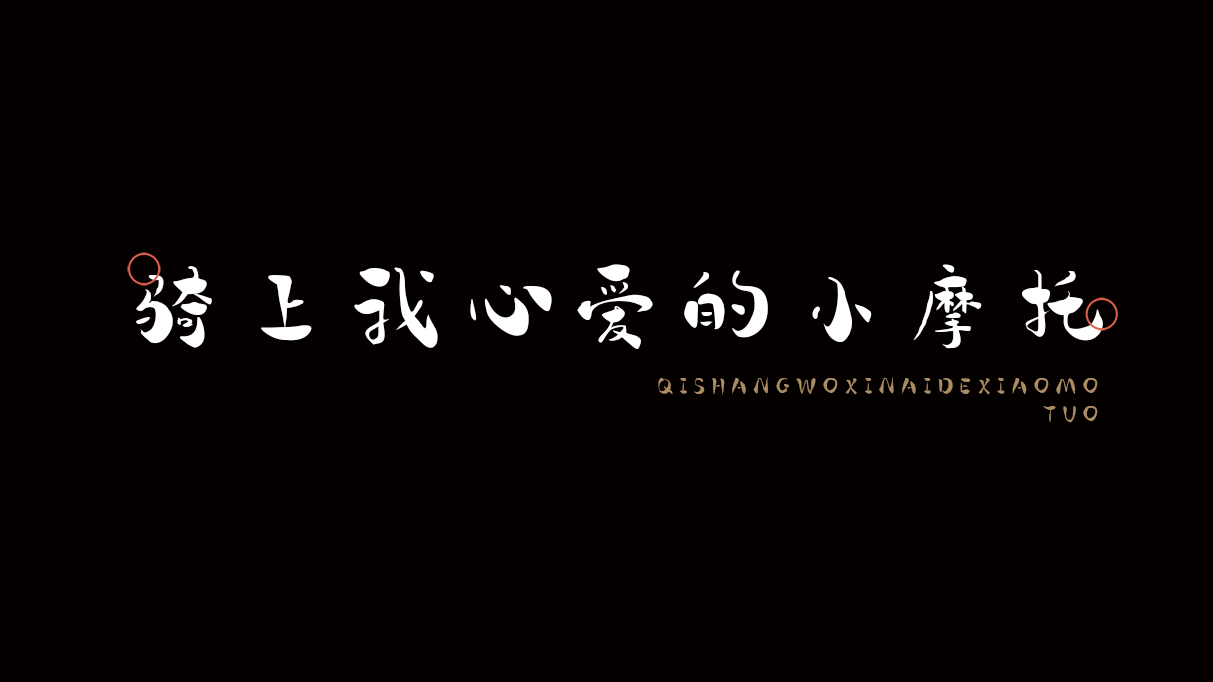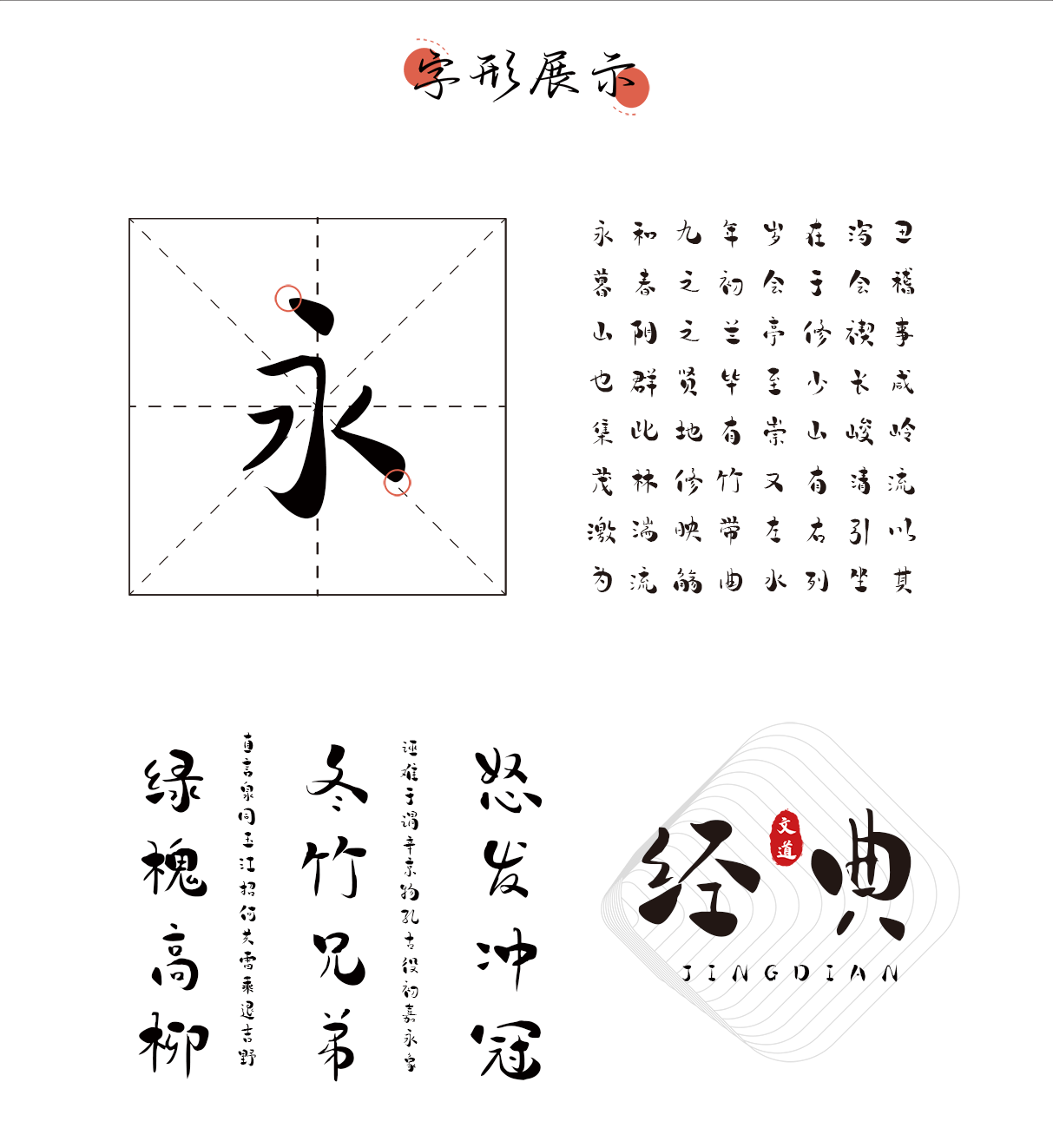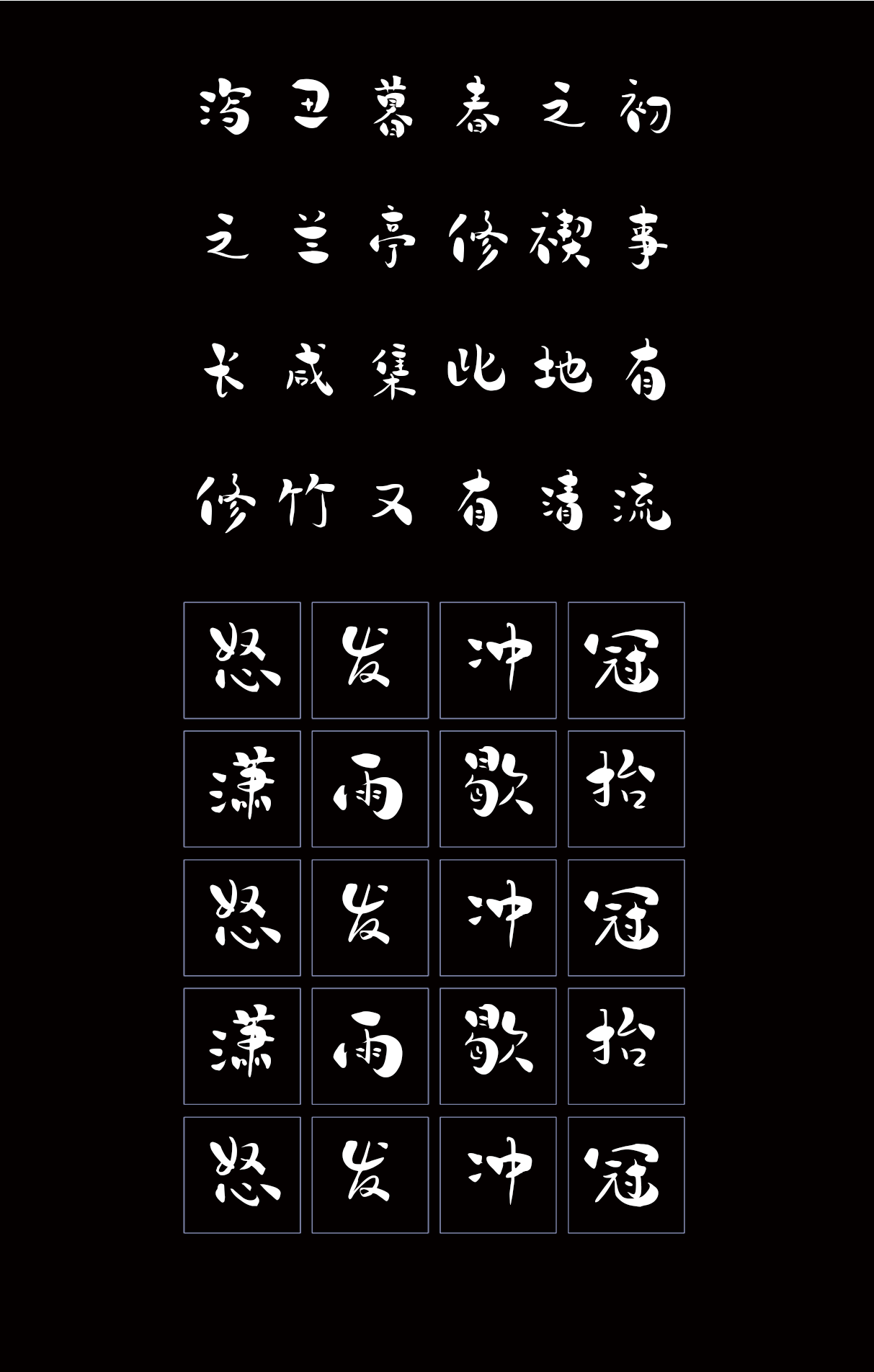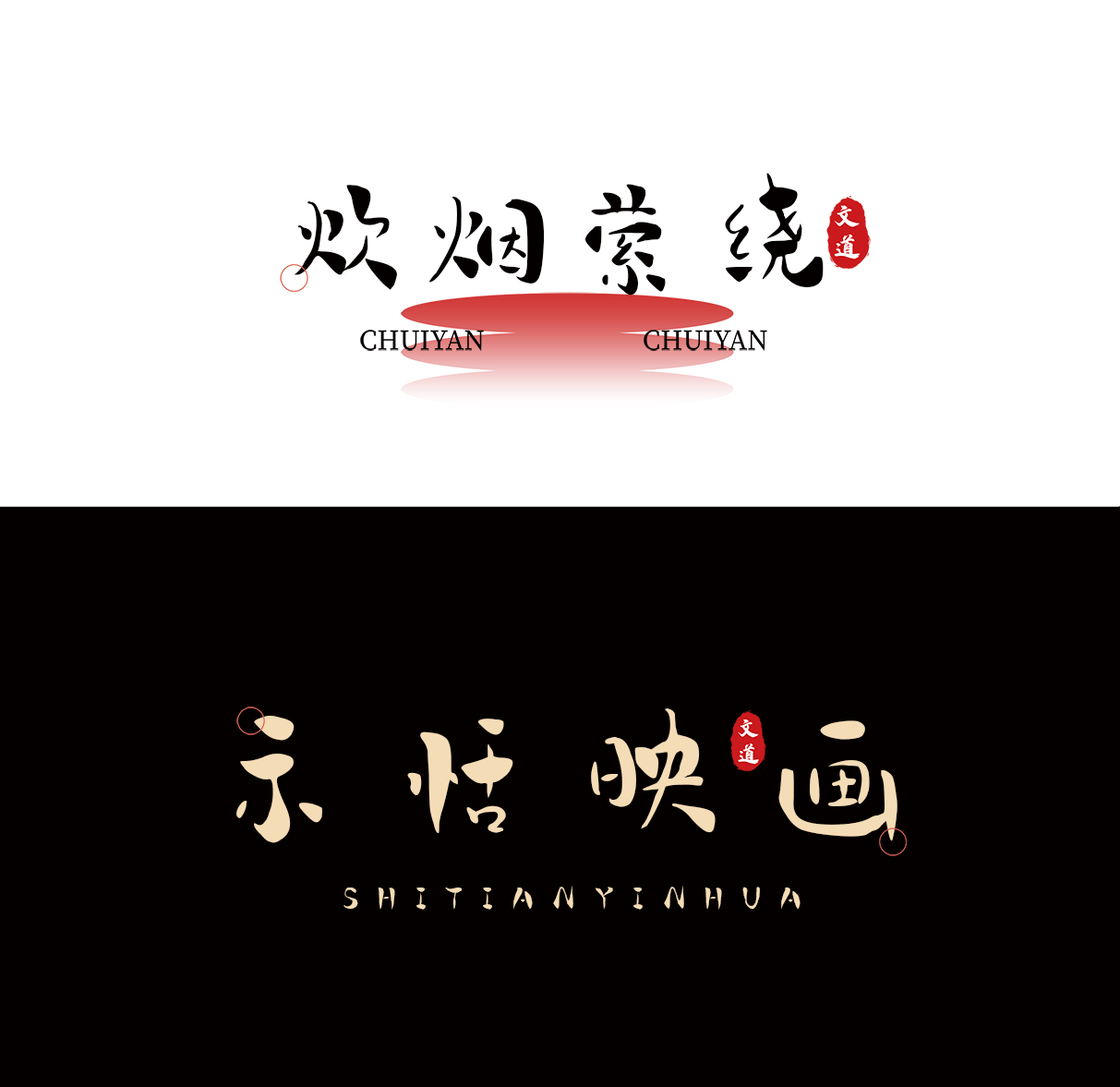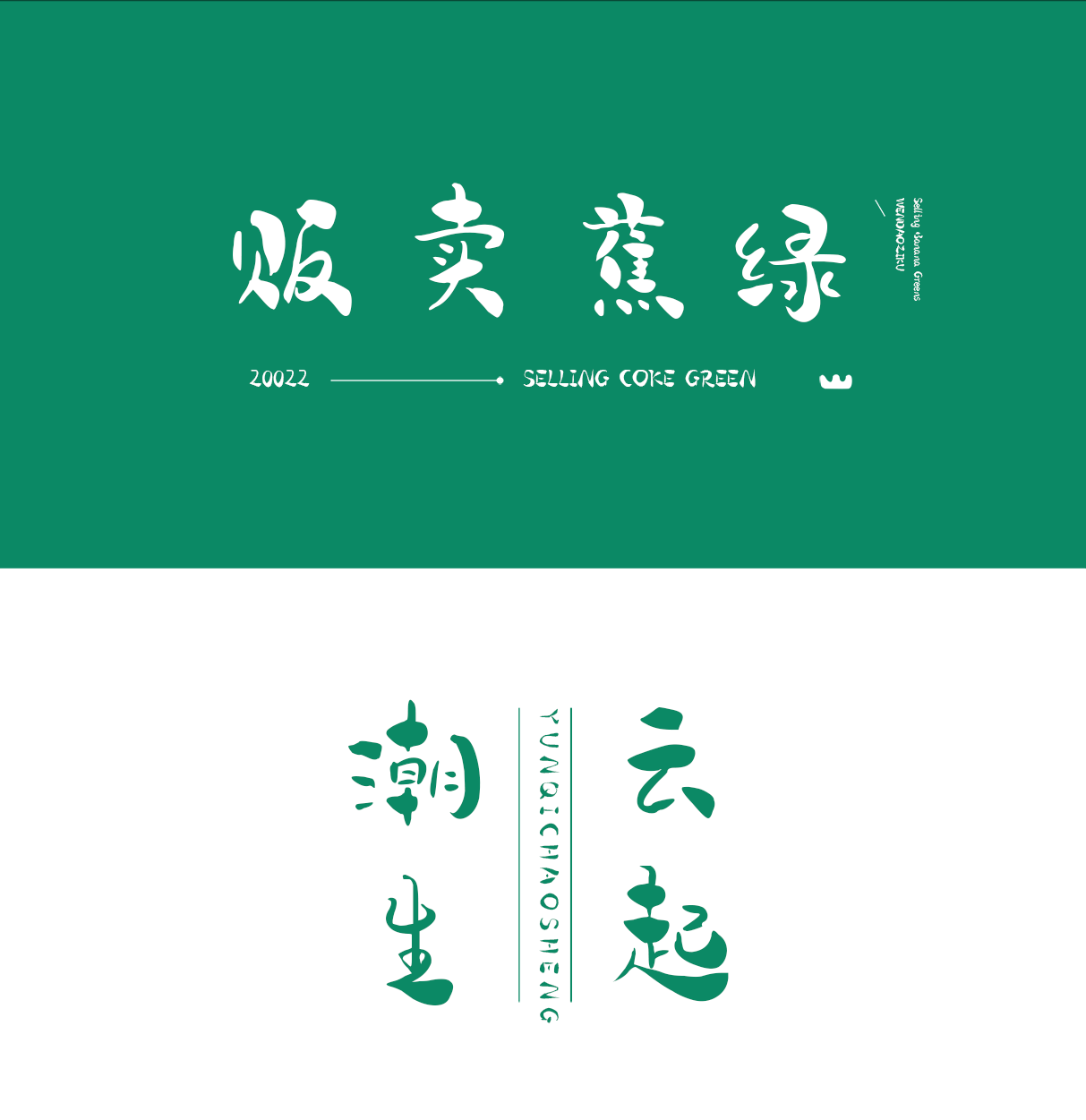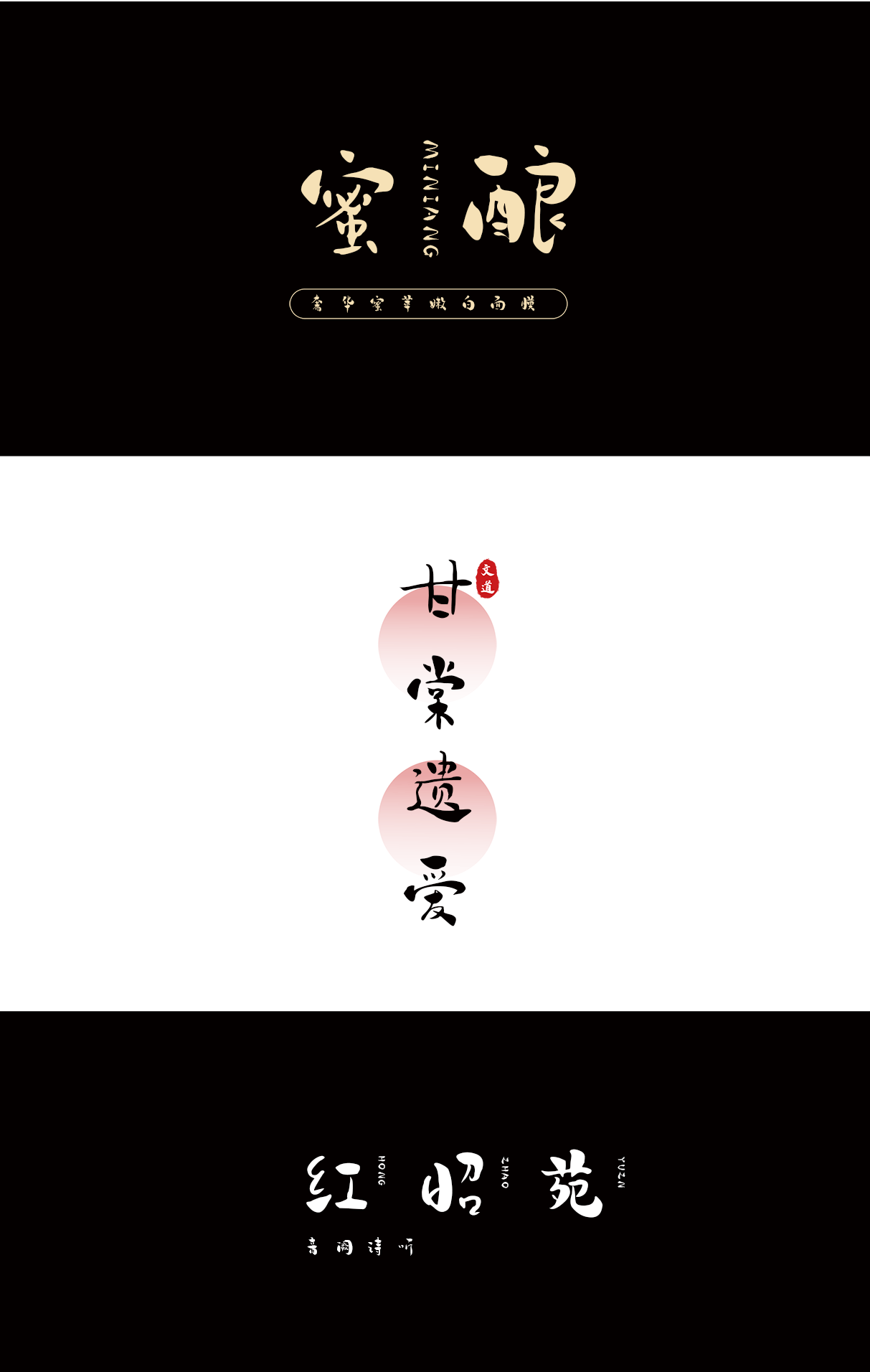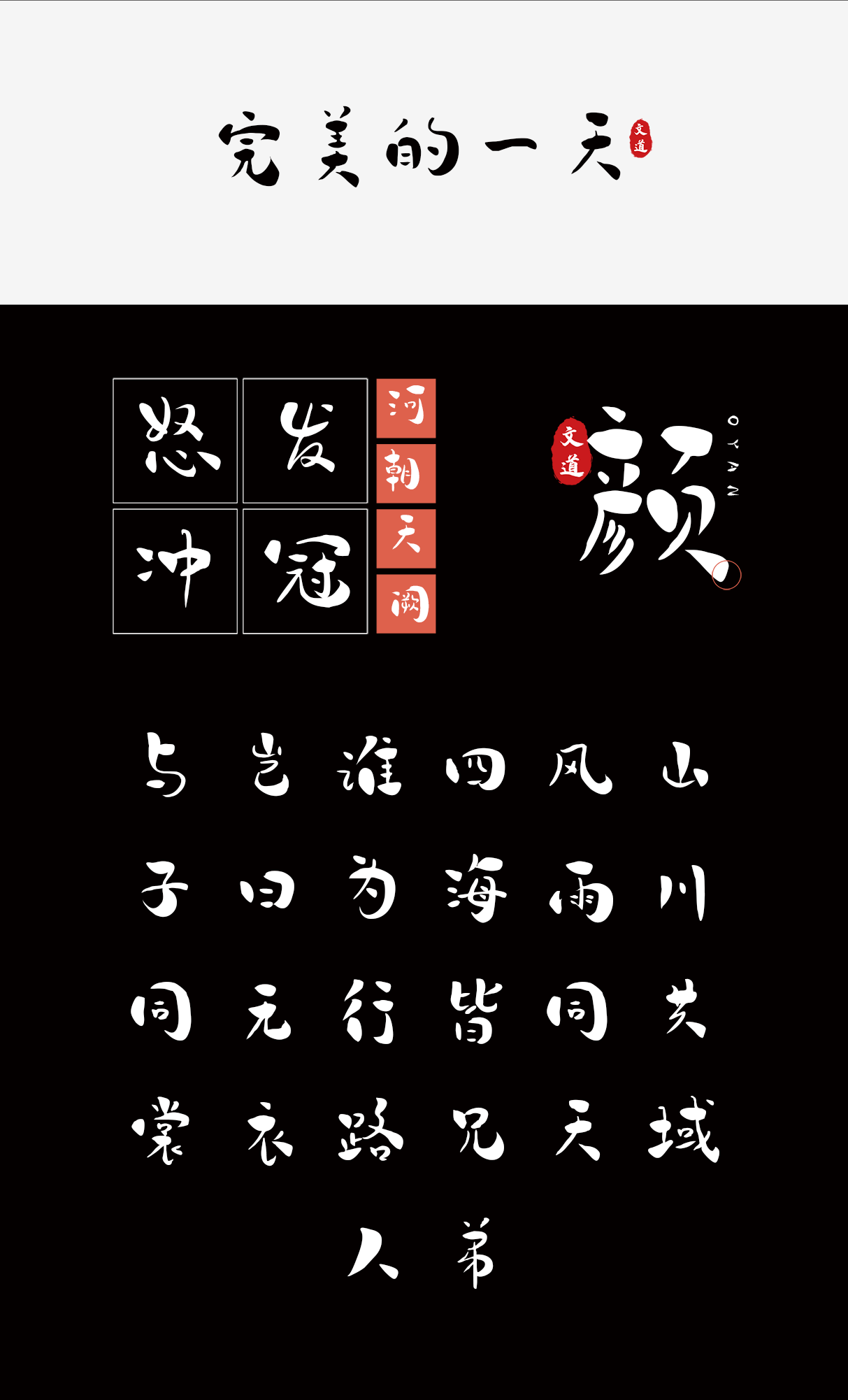
| 字体名称: | 骑上我心爱的小摩托 |
| 所属分类: | 创意体 毛笔书法 |
| 简介: | 骑上我心爱的小摩托是一款将书法与设计创意相结合的书写字体。这款字体以“传统元素”为肌理,通过对同类书法笔触的反复应用,形成强烈的动感。笔画左实右虚,笔触激越奔放。在飞扬豪放中透着几分风趣,适用于食品、酒类品牌的广告和产品包装设计,以及影视、动漫和游戏。 |